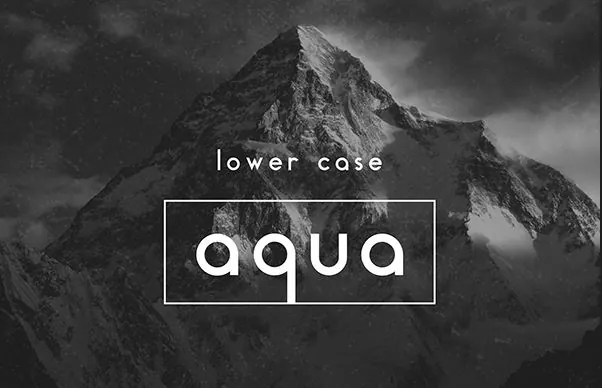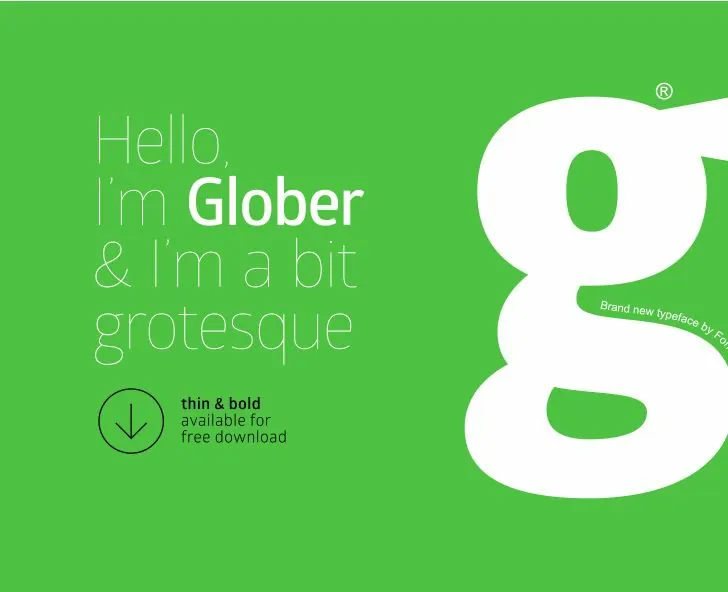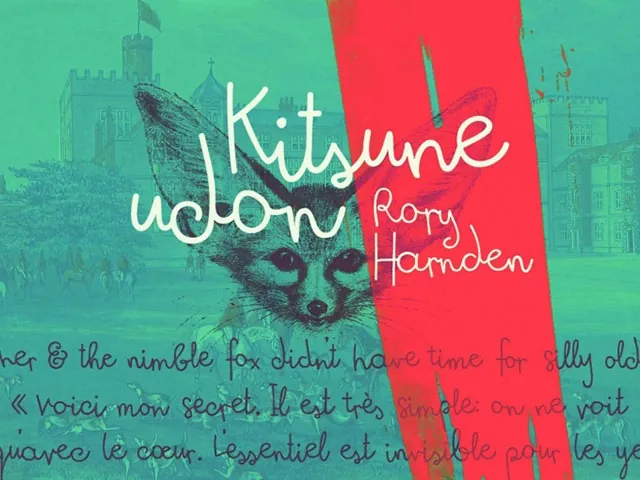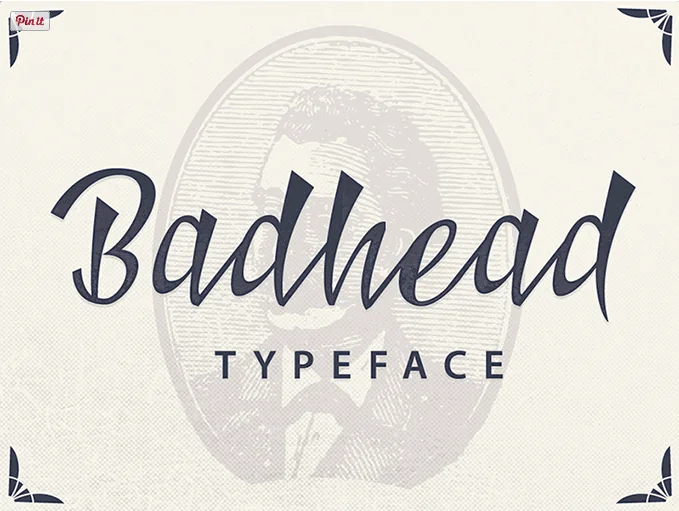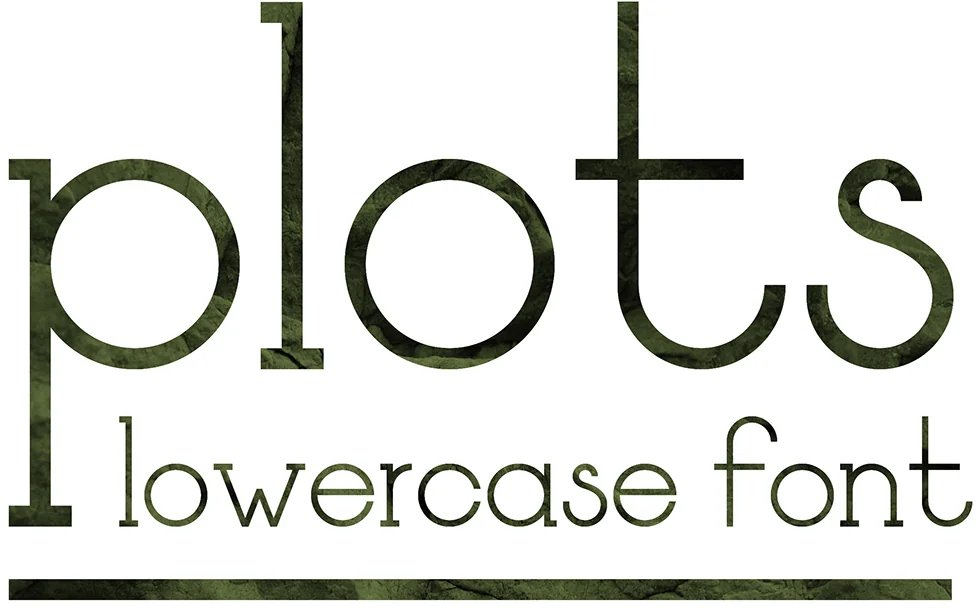
Continuamente hay nuevas tipografías o fuentes con nuevas formas o creatividades distintas. Corresponde al diseñador gráfico o web estar al tanto de estas nuevas fuentes para integrarlas en sus nuevos diseños y así diferenciarse de otros. Nuestro trabajo es de una evolución constante y sino estamos al día, nos quedaremos atrás.
En el mundo del diseño gráfico siempre es interesante conocer las nuevas fuentes que salgan. Y si encima salen nuevos diseños que sean gratis y con calidad mucho mejor. A los diseñadores nos gustan las fuentes nuevas, diferentes y que le den personalidad a nuestro trabajo. Un trabajo gana calidad o la pierde utilizando una u otra tipografía. Ahí está el trabajo del diseñador de utilizar la fuente adecuada.
En el artículo de hoy podrás ver nuevas tipografías gratis, para que estés al tanto de las novedades y de las nuevas creaciones tipográficas. Espero que te gusten y que las utilices desde ya en tus diseños. Podrás ver una colección de fuentes frescas, originales y distintas para tus diseños web. Si usas bien las tipografías en el diseño web consiguirás transmitir mejor. Hay muy buenas fuentes en la red pero muchas de ellas son caras, para que no incrementes el gasto en tu diseño te propongo esta selección de buenas tipografías para que te descargues gratis.
En este artículo pretendo mostrarte una selección de nuevas fuentes para que valores si merecen estar en tu próximo trabajo de diseño.
Silent Lips
Polya free font
Esta fuente es ideal para utilizar en titulares o encabezados, sobretodo para que se lea bien. Es una tipografía muy visual y creativa.
Fuente gratis Reis
Excelente tipografía tipo desgastado o pintada con brocha a mano.
Big John / Slim Joe – FREE Font
Otra fuente excelente para titulares.
Groninger
Docker
Loque
Fuente decorativa, no es para utilizar en textos sino de forma puntual y esporádica por su difícil lectura.
Modeka
Tipografía muy fina.
Belepotan
Masaaki free font
Tipografía tipo pixel.
Moriarte
Fuente muy original, las letras están como desviadas mediante un corte. Ideal para utilizar en temas de sustos, miedo, o simplemente para diferenciarse.
Pirou free font
Esta tipografía está diseñada para titulares, posters, o logos.
Arca Majora
Fuente que se lee perfectamente. Impactante.
Furgatorio
Noticia Text
Deibi
Weston
Satellite
Retro
Null
Infinity
Homestead
Orbitrom
Ribbon
Sniglet
League Gothic
Lavandería
Blanch
rbno2
Barnstormer
Kocoon Light Free Font
Shivaji
The Cat has a Hat font
Rock Salt Font
Dino Font
The Medic
Uni Sans Free
Orlando Typeface
Bizarre
Gasalt
Nulshock font
Finity Font
Meticulous Ariel
Kitsune Udon free font
Facile Sans Font
Thin Line Font – Free font
L’egoist Corbeau free font
Es una tipografía gratuita inspirada en París y en el art deco.
Hans Kendrick Regular free font
Es una fuente de palo y de un peso intermedio. Está bien para titulares.
La Chatte à Maman
Groteskia
Esta fuente es de palo, larga y bastante potente para titulares impactantes.
Typoster
Esta fuente es gratis para uso personal y tiene los caracteres españoles.
Evogria
Otra fuente para que utilices en titulares.
Building
Otra fuente con gran impacto visual.
s-arial
Rimouski bold
Simplifica
Como su nombre bien dice es una fuente de líneas simples.
Aqua
Tipografía de líneas rectas pero redonditas.
Farray
Te la recomiendo para que utilices para titulares. Tiene mucha fuerza.
Look up
Tipografía muy original compuesta por flechas.
Camptom
Las 18 familias no son gratis pero la light y bold sí lo son.
Glober
Las fuentes fina y gruesa son para descargar gratis.
Mohave
Tipografía de líneas rectas.
Disclaimer
Mi consejo es que la utilices para títulos o con poco texto, porque si abusas de ella, será difícil de leer.
Tesla
Otra tipografía para utilizar en títulos o texto a resaltar.
Paragon Font
La tienes en dos estilos: más fina y más ancha. Para texto es recomendable la más fina, pero para títulos lo ideal es utilizar la segunda.
Noir font
Otra fuente que la tienes en dos anchuras diferentes.
Pretender
Una tipografía ideal para utilizar en titulares.
Rakesly
Esta fuente la tienes en cursiva, negrita, extrafina,…
Alanus
Retrospective
Tomb Raider
Yeah Papa Font
Fuente del estilo manuscrito a mano.
Belladona
Es una tipografía vintage. La tienes en dos formatos ttf y otf.
Yarin
Badhead
Excelente fuente tipografía fácil de leer y en formatos otf, ttf, eot, svg, woff y woff2.
Tipografía de estilo desgastado, con texturas adecuadas da la impresión de que las letras están formadas en una piedra.